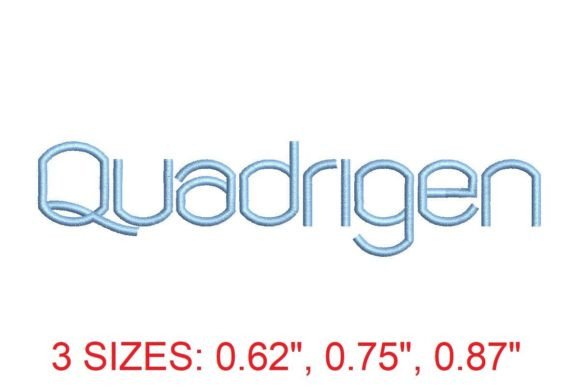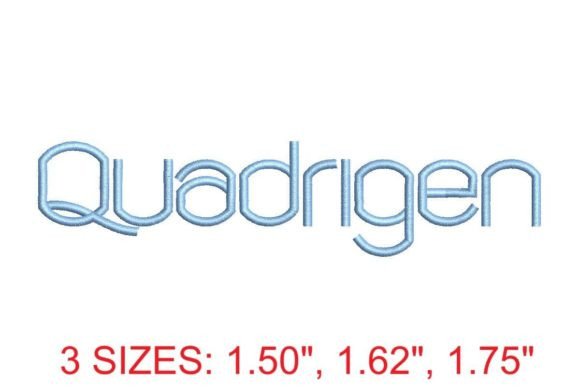
Quadrigen Embroidery Font
Die richtigen Designelemente zu finden, kann eine Herausforderung sein, aber Quadrigen Embroidery Font bietet eine außergewöhnliche Sammlung, die Ihre Arbeit sofort aufwertet.
Mit Präzision gefertigt, bietet Quadrigen Embroidery Font saubere Vektoren, eine reibungslose Typografie und eine kommerzielle Lizenz für ein beruhigendes Gefühl.
Egal, ob Sie POD-Produkte (Print on Demand), Hochzeitseinladungen oder Social-Media-Grafiken erstellen, Quadrigen Embroidery Font ist die ideale Wahl.